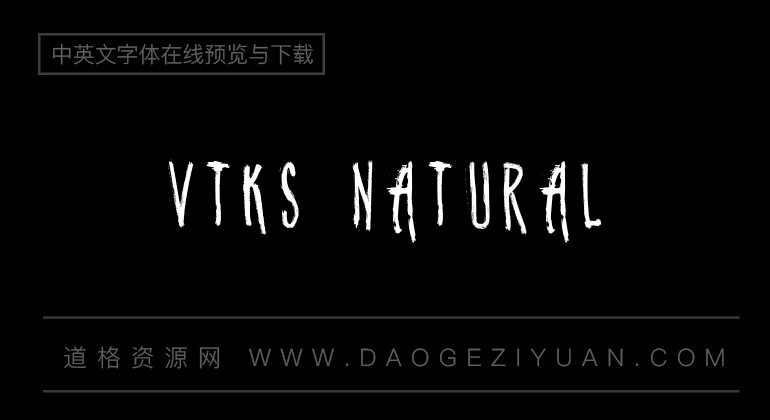
? Vtks Natural字体是一款拥有自然质感的手写字体。它具有温暖的色调,细腻的线条,自然的笔画,清晰的细节,以及舒适的可读性。Vtks Natural字体可用于任何个性化的设计,特别是适合用于卡片,海报,婚礼,礼物,品牌标识,婚礼邀请,插图,标题等。内容介绍
Vtks Natural是一款非常不错的手写艺术字体,具有很好的视觉感,适合于文化类的宣传设计、商业类品牌的广告和产品包装设计以及个性化文字排版等较多场景。